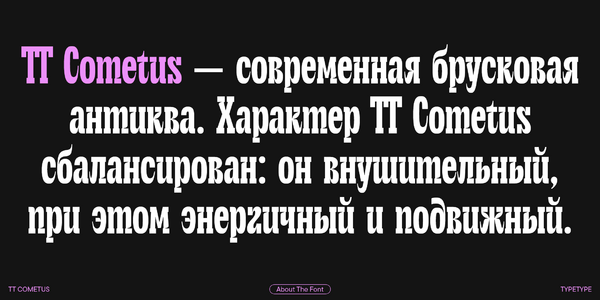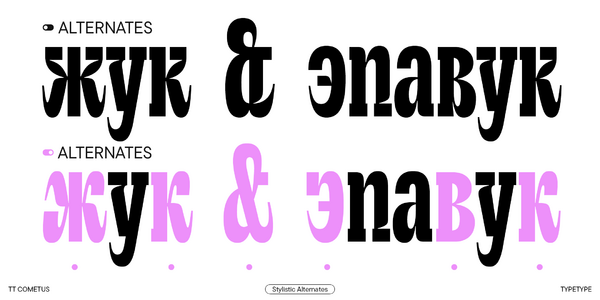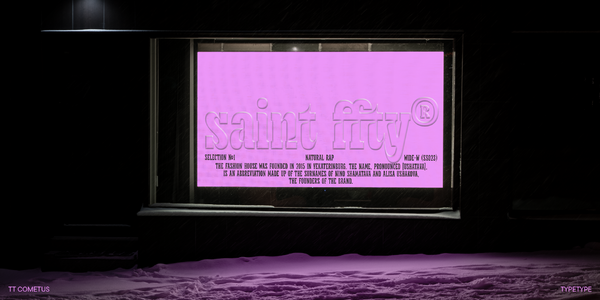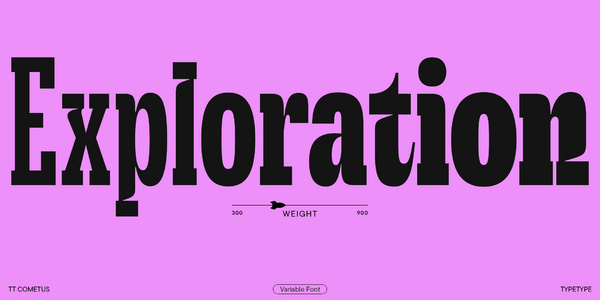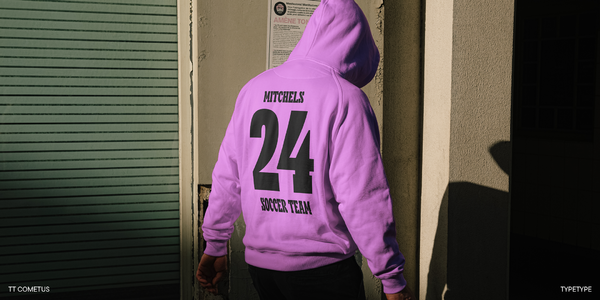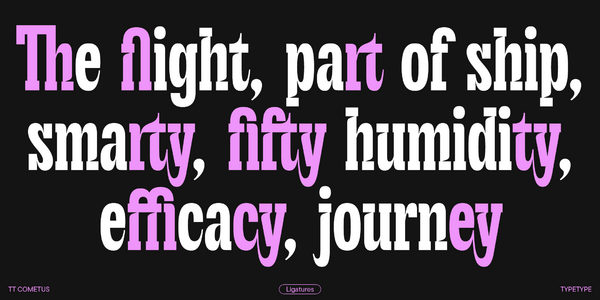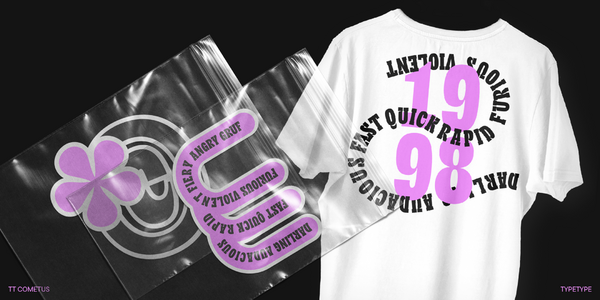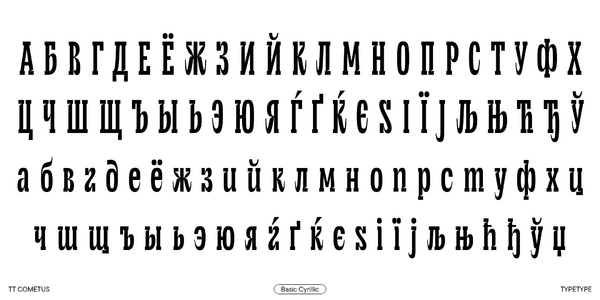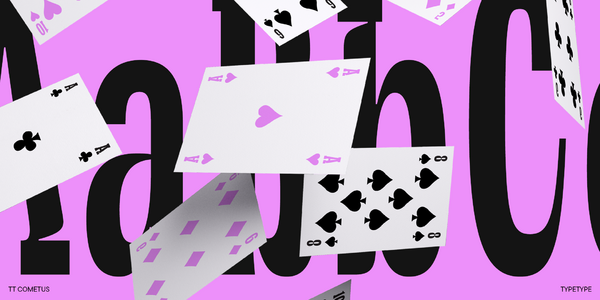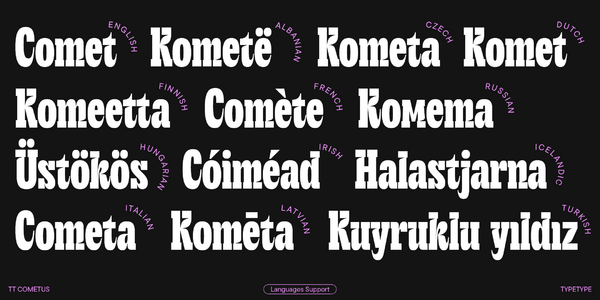
TT Cometus
TT Cometus — ТТ Кометус
Произносится «ТТ Кометус». «Cometus» — производное слово от comet, в переводе с английского «комета». Буквы «TT» являются аббревиатурой названия компании.
TT Cometus — яркая брусковая антиква. Это внушительный и солидный, при этом энергичный и подвижный акцидентный шрифт.
TT Cometus
Название шрифта отсылает нас к образу кометы
Изначально шрифт TT Cometus задумывался как узкая брусковая антиква для акциденции. Если обязательным условием для создания брускового шрифта являются мощные и тяжелые засечки, то почему бы не попробовать соединить их с прямо противоположными формами и сделать шрифт более подвижным? Так у TT Cometus появились характерные подсечки в местах соединения вертикального штриха с засечкой. Эти подсечки нужны были чтобы сделать шрифт более рукотворным, не машинным, а также создать напряжение в элементах букв и задать важные акценты.
TT Cometus — это гарнитура из 5 шрифтов: Light, Regular, Bold, Black и Variable.
Лучше всего шрифт работает в крупном кегле. Это точно не нейтральный шрифт!
О гарнитуре TT Cometus
Поддержка языков 230+
Встречайте TT Cometus версии 2.0 — теперь с поддержкой кириллицы! Значительно расширили кассовый состав и усовершенствовали техническую составляющую этого яркого шрифта.
TT Cometus — современная брусковая антиква. Название гарнитуры отсылает к образу кометы — мощного увесистого тела с красивым хвостом, грациозно рассекающего космические просторы с огромной скоростью. Это ключ к пониманию шрифта.
Характер TT Cometus сбалансирован: он внушительный и солидный, при этом энергичный и подвижный. Создавая его, мы хотели сохранить свойственные для слабов тяжелые засечки, но при этом сделать шрифт актуальным и динамичным. Поэтому мы соединили устойчивые детали с прямо противоположными формами и добавили ощущение рукотворности, вдохновляясь движениями кисти в каллиграфии.
Так, TT Cometus отличают заостренные терминалы, напоминающие хвосты комет. Особенно они заметны в буквах «с», «у», «е» и «t». Еще одна интересная деталь — фигурные влития арок и полуовалов, придающие шрифту пластичность. А мощные засечки позволяют ему оставаться устойчивым. Контраст между толщинами горизонтальных и вертикальных элементов небольшой, но в засечках, влитиях и окончаниях букв он ярко выражен.
В обновленной версии гарнитуры появилась долгожданная поддержка русского языка и новые стилистические сеты, увеличилось количество OpenType фич, полностью обновился кернинг и улучшился хинтинг.
TT Cometus лучше всего проявляет себя в крупном кегле. Это точно не нейтральный шрифт! Он притягивает к себе взгляды и безупречно выглядит в заголовках, логотипах и брендинге — в общем, везде, где нужно привлечь внимание.